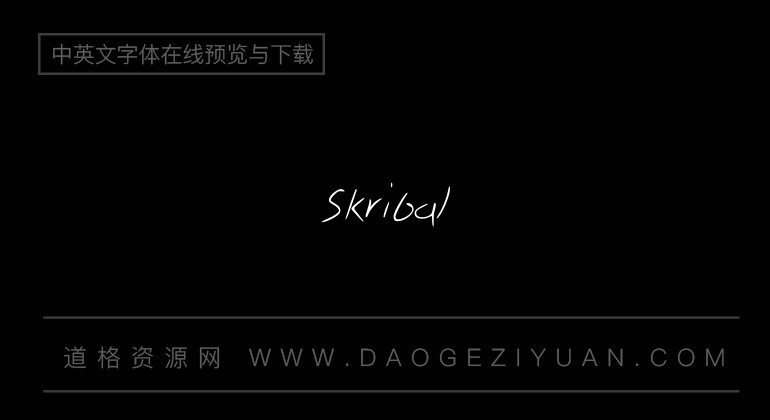
Skribal
Skribal字体是一种手写风格的字体,具有独特的风格和个性化的特点。Skribal字体的每个字母都像是由手写笔创造出来的,具有独特的流畅感和自然感。这种字体适用于多种设计场景,如印刷品、海报、广告等等,可以为设计师带来更多的创意和灵感。此外,Skribal字体还提供了多种不同的粗细和风格,以满足不同设计需求的要求。总的来说,Skribal字体是一种富有个性和创意的字体,可以为设计师提供更多的选择和灵感。
Skribal是一款非常不错的手写艺术字体,具有很好的视觉感,适合于文化类的宣传设计、商业类品牌的广告和产品包装设计以及个性化文字排版等较多场景。